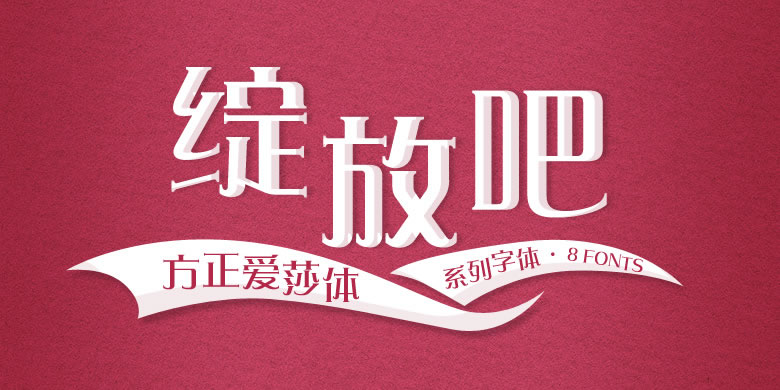
方正爱莎体家族
方正爱莎体家族,这款字体结构工整、笔画清晰,兼顾美观与易读性,适用于标题、正文、海报、包装、LOGO 等多种场景。字形优雅稳定,风格百搭耐看,适配日常排版与创意设计,让文字呈现更舒适、更具质感。方正爱莎体家族一笔一画,皆是细节,以均衡的比例、流畅的线条打造舒适视觉体验,字形端正大气,风格简约现代。无论是商业设计、品牌宣传还是日常排版,都能轻松驾驭,让文字更有格调与力量。方正爱莎体家族字体下载。
一款非常优美的字体,它能表达女士的温柔典雅,高贵和魅力,充满时代感,适合女性化妆品牌、时装和健康产品等宣传。